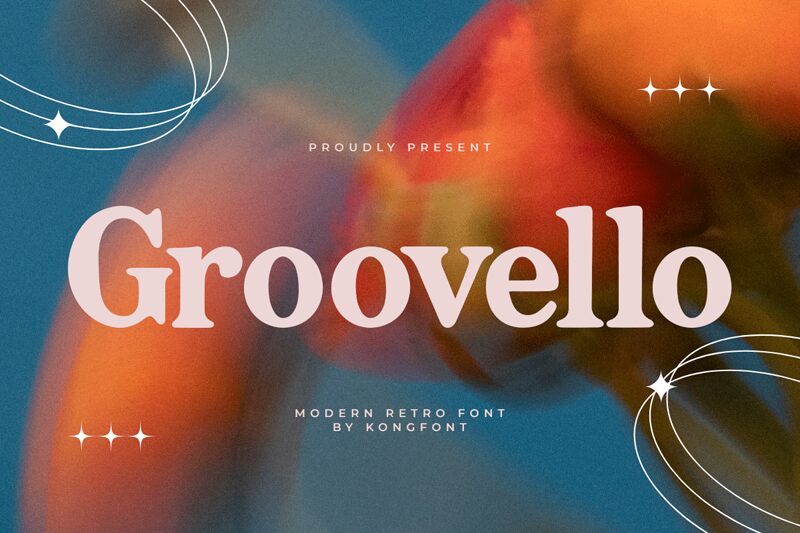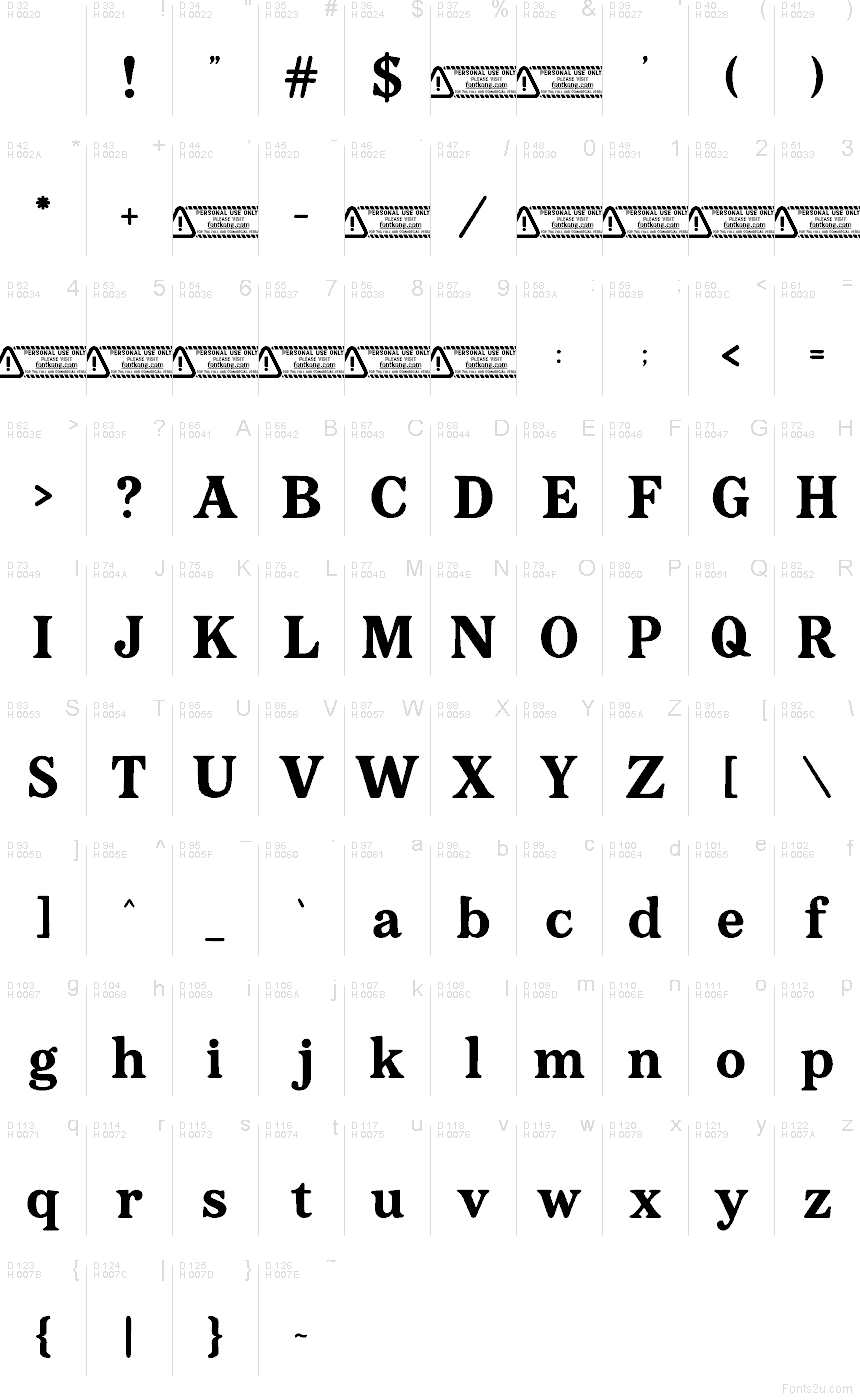
Groovello von Kong Font ist eine kostenlose Retro-Serifenschrift mit dem lässigen Flair der 70er-Jahre-Lounge-Ära. Die Buchstaben kombinieren wuchtige, abgerundete Formen mit verengten Verbindungen und geschwungenen Details – das verleiht der Schrift eine entspannte, fast theatralische Note, ganz ohne steif zu wirken.
Sie passt perfekt für Plakatüberschriften, Branding im Album-Stil, Café-Speisekarten, Verpackungsdesigns und Cover-Texte, bei denen man eine warme Vintage-Atmosphäre erzeugen möchte, ohne dabei zu sehr ins Verspielte abzugleiten. Als kostenloser Font eignet sie sich zudem hervorragend für Titelschriftzüge und kurze Wortmarken: Die prallen Kurven und die kleinen, geschwungenen Serifen sorgen selbst bei kurzen Texten für einen relaxten, groovigen Rhythmus.